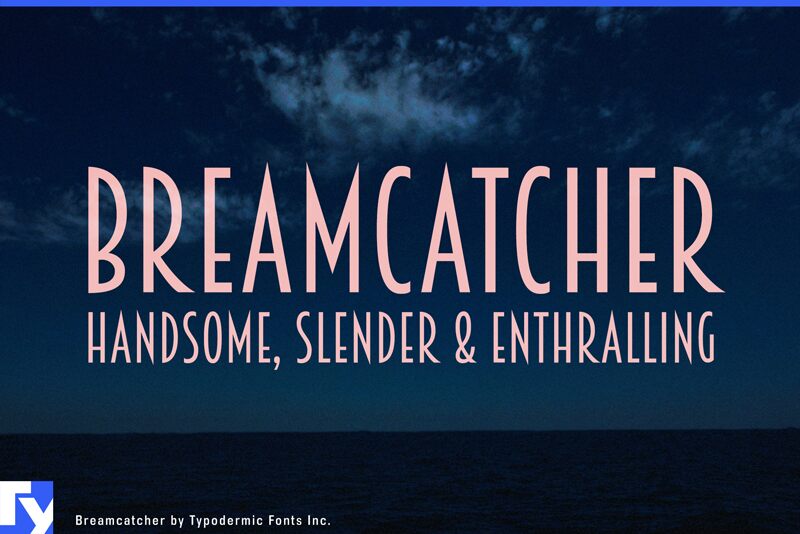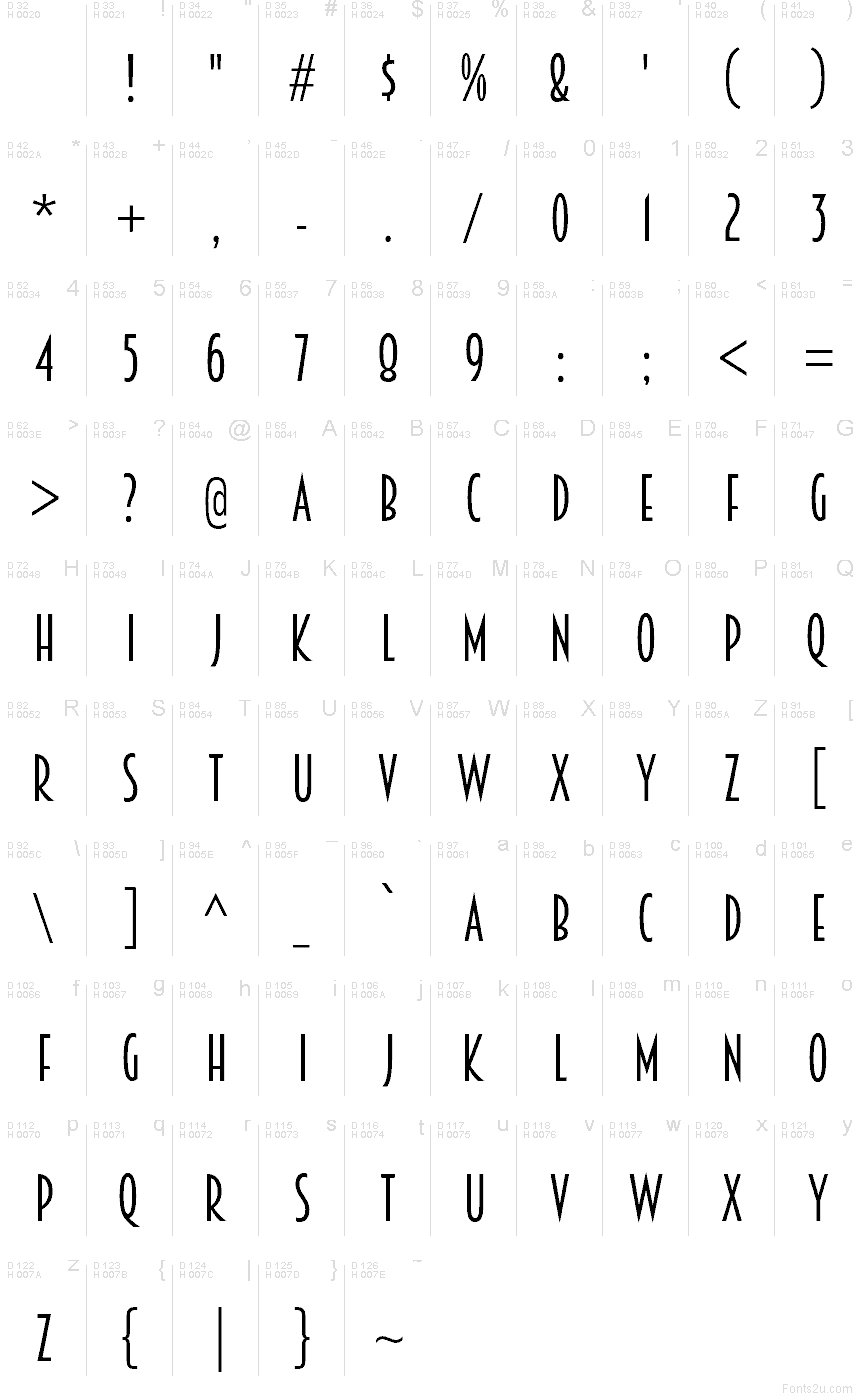
Breamcatcher oddaje elegancję art déco lat 20. XX wieku, wprowadzając ją do zestawu narzędzi współczesnego projektanta. Jego wysokie, smukłe formy i wdzięczne łuki przywodzą na myśl powagę minionej epoki, a subtelne nieregularności sprawiają, że pozostaje ciepły i ludzki — nigdy zimny czy mechaniczny. Swobodny odstęp między znakami daje każdemu z nich przestrzeń do oddychania, tworząc na stronie spokojny, pewny rytm. Musisz oszczędzić miejsce? Zmniejsz odstępy między literami i obserwuj, jak Breamcatcher się dostosowuje, nie tracąc swojego uroku.
Breamcatcher, dostępny obecnie w wszechstronnym zakresie wag i stylów, oferuje jeszcze więcej sposobów na wniesienie swojej charakterystycznej wyrafinowanej formy do Twoich projektów. Użyj lżejszych stylów, aby uzyskać zwiewną, powściągliwą elegancję; przełącz się na odważniejsze warianty do nagłówków, które przyciągają uwagę bez krzyku. Niezależnie od tego, czy jest ustawiony jako prosty, czy kursywa, proporcje Breamcatcher pozostają nienagannie zbalansowane. Ten krój pisma doskonale sprawdza się w zastosowaniach, gdzie liczy się wyrafinowanie: luksusowy branding, eleganckie menu, układy redakcyjne, zaproszenia na wydarzenia oraz opakowania wymagające odrobiny ponadczasowego wdzięku. Dzięki obsłudze większości europejskich języków opartych na alfabecie łacińskim, greki i cyrylicy głos Breamcatcher niesie się z równą siłą ponad granicami.
W świecie, który często pędzi obok detali, Breamcatcher zaprasza czytelnika do zwolnienia tempa, rozsmakowania się w przestrzeni między literami i zatrzymania się na chwilę dłużej przy Twojej wiadomości. To typografia jako doświadczenie — wyważona, pełna wdzięku i niezapomniana.